草体关键有章草、今草、狂草三种。草体是在东汉秦文隶变之后各种各样新老草化书写的基本上慢慢产生的。草体产生的突破口是为求好用而将篆书撰写速率加速,进而“散伙隶体”,出現拿笔绵延、点画省简、偏旁部首假借等技法、结构类型。
1.章草
章草是篆书的草写,即初期含有隶意的草体,拿笔绵延省简,技法、体势较篆书丰富多彩变化多端。同之后的今草对比,章草犹存隶意,很多字还变向保存着篆书的横着取势和波挑技法,各字尺寸较为匀称,字的笔画连同较少且仅限一字以内,故字字单独(这与汉朝用小笔在窄小的简牍上写草字相关)。章草产生于汉朝末期。至汉朝,章草已较时兴,出現刘睦、杜操、崔瑗等草体名人和汉未以张芝为意味着的草体派系。张芝作品的章草已彻底标准。蜀国皇象《急就篇》、汉朝索靖(出师颂》等,承继了张芝至今的标准书写,通常借明显的波挑呈现飞舞洒脱之势,章草亦因而迈向类型化。
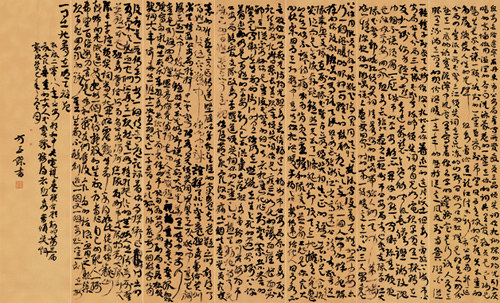
2.今草
今草由章草发展趋势而成,少了章草的波挑,改横着取势为竖向贯气,体势趋向纵长、鼓侧、摇缀,字型尺寸错综,左右字笔法映衬、偶有拖累,撰写更为流便,体势更加开朗。今草出現后,原先含有波挑、字字单独的草体方被称作“章草”。纸型的普及化,促进了章草向今草的演变。魏晋《济白守残纸》、《为世主残纸》及卫瓘〈顿州帖》、陆机《平复帖》等章草著作,均有向今草衔接的显著发展趋势。纯碎的今草出現于晋代,王羲之最后健全了今草。今草经典作品有王羲之〈寒切帖〉、《十七帖》,唐朝孙过庭《书谱》等。狂草、大草出現之后,别称今草为“绿草”。理论的今草包含绿草、大草、狂草。
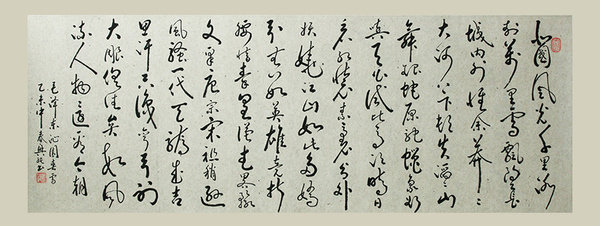
3.狂草
狂草起源于唐朝王玉,由今草向狂肆的方位演变而成,笔法绵延,放纵不羁,一笔数据,气贯逐行。狂草与大草有时候混称,二者仅有狂放水平之别,均难识别。狂草一派神行,无行无列(摆脱队伍界线),大草则虽放犹有控制。大草名人除王玉外,也有与“颠张”合称的“醉素”一一唐朝怀素人上人及其宋朝黄山谷、明祝枝山、明末清初王铎等。